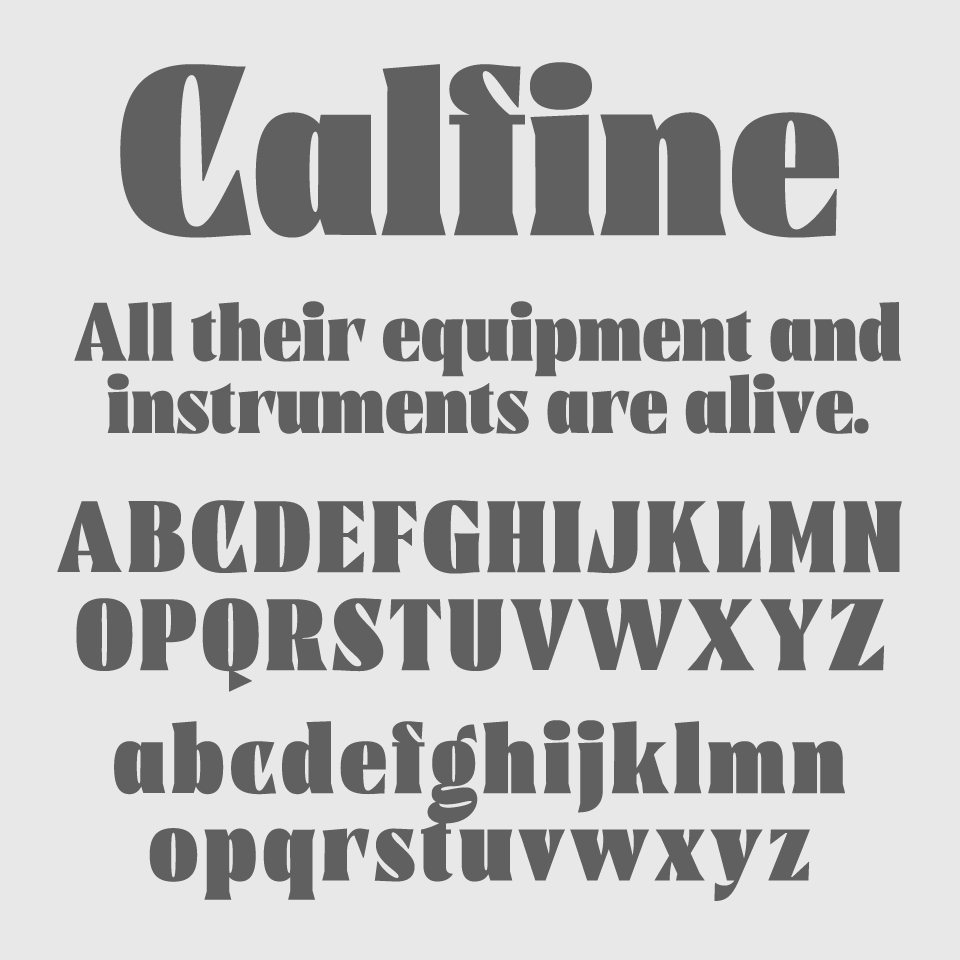
Calfineフォントは、ふっくらとしたやわらかい骨格にシャープなエッジがきいた、どこかユーモラスなセリフ体フォントです。抑揚のあるフォルムが見ていて心地よく、親しみのある表情をしています。
少しクセのあるバランス感が個性的で、クラフト感のある紙ものや、ゆったりとした雰囲気のブランドにもよく似合う、ぬくもりを感じさせるフォントです。